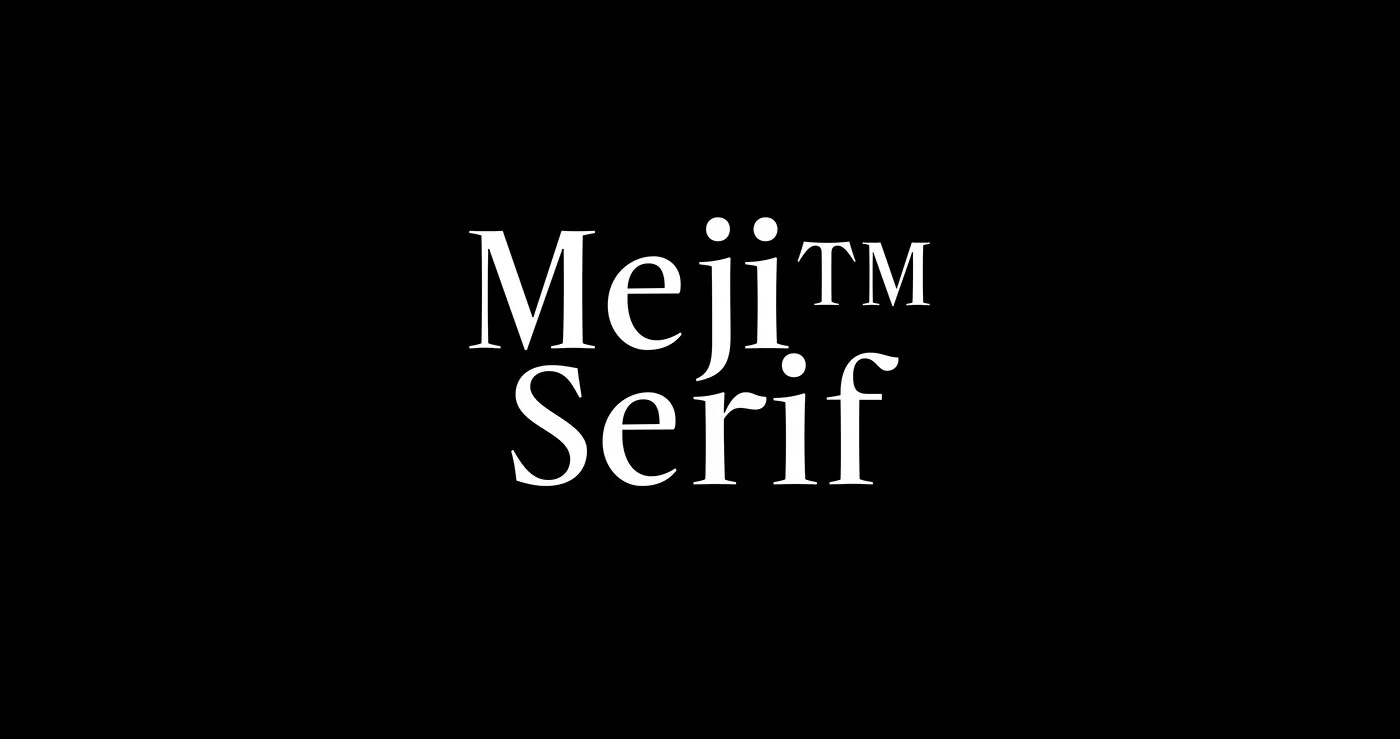
Meji™ Font
A Meji™ Serif é uma elegante fonte serif que oferece uma combinação única de modernidade e nostalgia. Perfeita para logotipos, revistas e mídia social, ela está entre as últimas criações na nossa coleção de fontes digitais. Com oito pesos (extralight, light, regular, medium, semibold, bold, extra bold e black) e duas estilos diferentes (normal e italic), essa fonte é uma escolha perfeita para qualquer projeto gráfico que exija precisão e estilo. Composta por apenas 99designs, a Meji™ Serif é tanto moderna quanto nostálgica, tornando-se uma opção versátil para designers de todos os perfis, desde aqueles procurando pelaquímica perfeita entre diferentes estilos até aqueles que buscam um olhar clássico em projetos atuais. Com sua vasta gama de pesos e estilos, a Meji™ Serif é uma escolha ideal para qualquer projeto que exija graça e robustez.